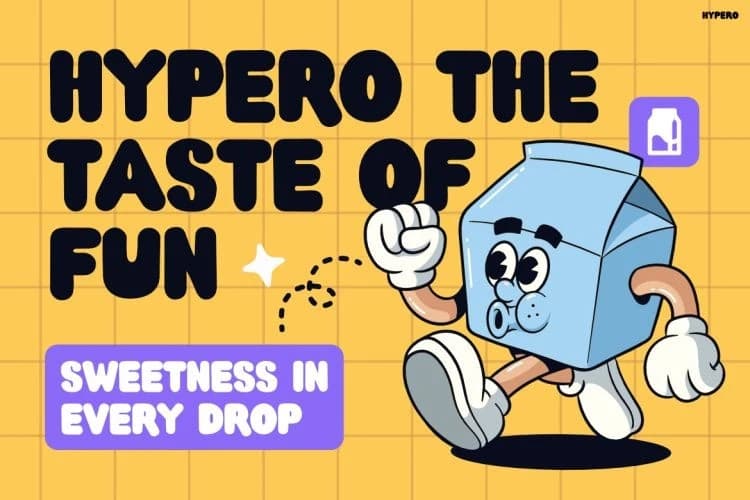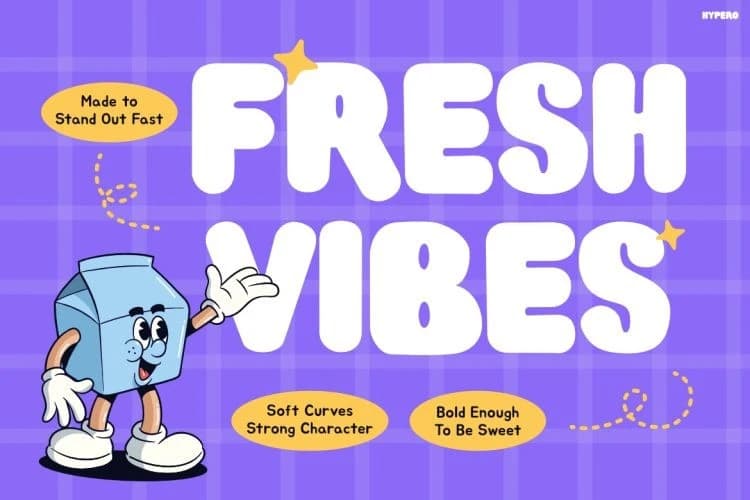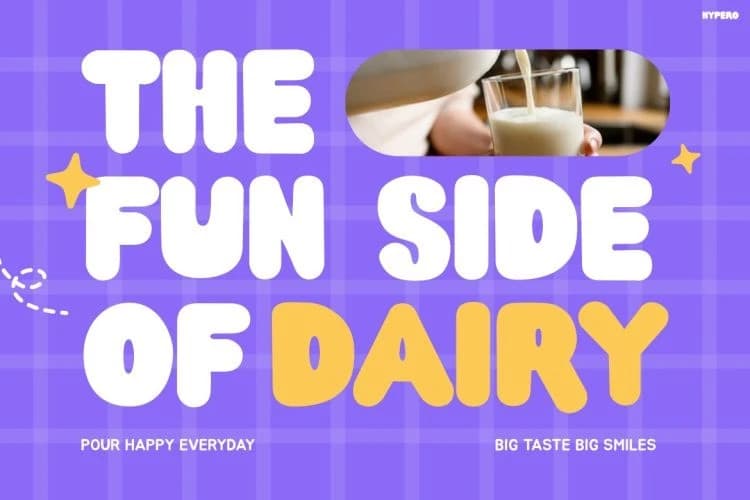
Hypero Oyuncu Yazı Tipi
Hypero Playful Font, tüm projelere eğlence, mutluluk ve enerjik bir hava katmak için tasarlanmış kalın balon gösterim yazı tipi. Retro karikatürlerden, atıştırmalık ambalajlarından, neşeli maskotlardan ve neşeli marka kimliğinden ilham alan bu yazı tipi, anında canlı ve göz alıcı bir görsel etki yar
Hypero Playful Font, her projeye eğlence, mutluluk ve enerjik bir hava katacak şekilde tasarlanmış kalın balon gösterim yazı tipidir. Retro çizgi filmlerden, atıştırmalık paketlerinden, eğlenceli maskotlardan ve neşeli marka kimliğinden ilham alan bu yazı tipi, anında canlı ve göze çarpan bir görsel etki yaratır.